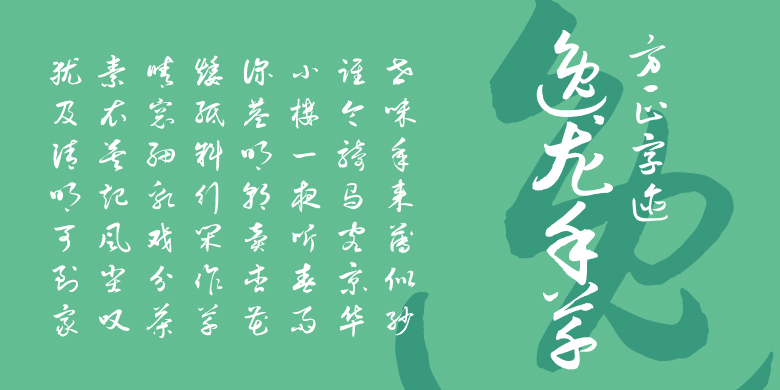
方正字迹-逸龙手草
刘龙斌
行书、草书、常规书写·毛笔
逸龙手草,承袭逸龙体书法一贯的飘逸之风,在严格遵循传统草书创作手法的基础上,融入了一些现代简化字草书特色,目的是为了提升更高的辨识度,方便更多人群使用。该字体在笔划上追求线条匀称,干净利落,笔力遒劲;在字形结构上体现联结流畅,协调自然,首尾呼应,顾盼生姿,行云流水,有种翩若惊鸿,婉若游龙之感,不一而足。逸龙手草集传统而现代,融百家之长,成一家之奇。必将历久弥新,字游世界,成为当代新风清流之书体!